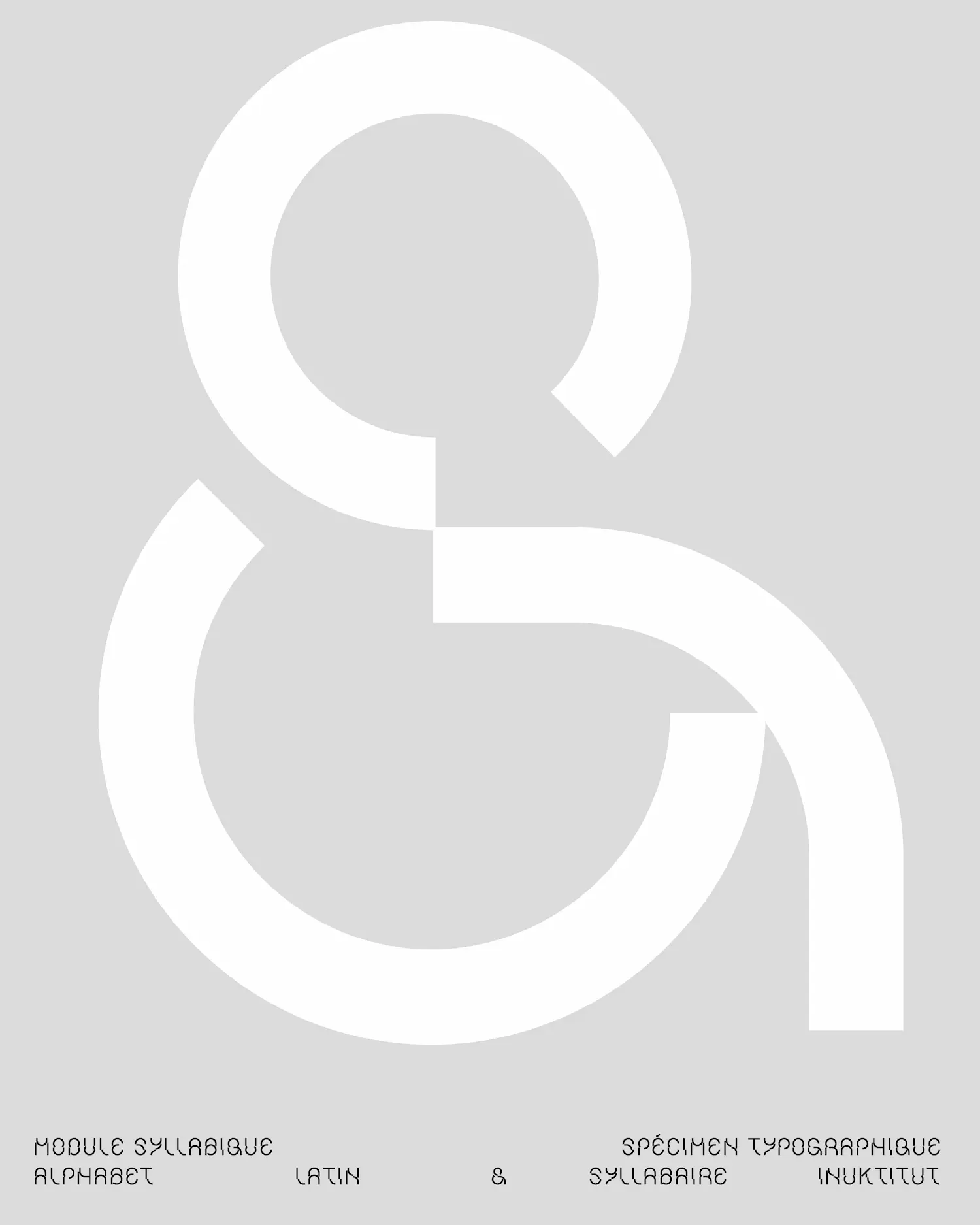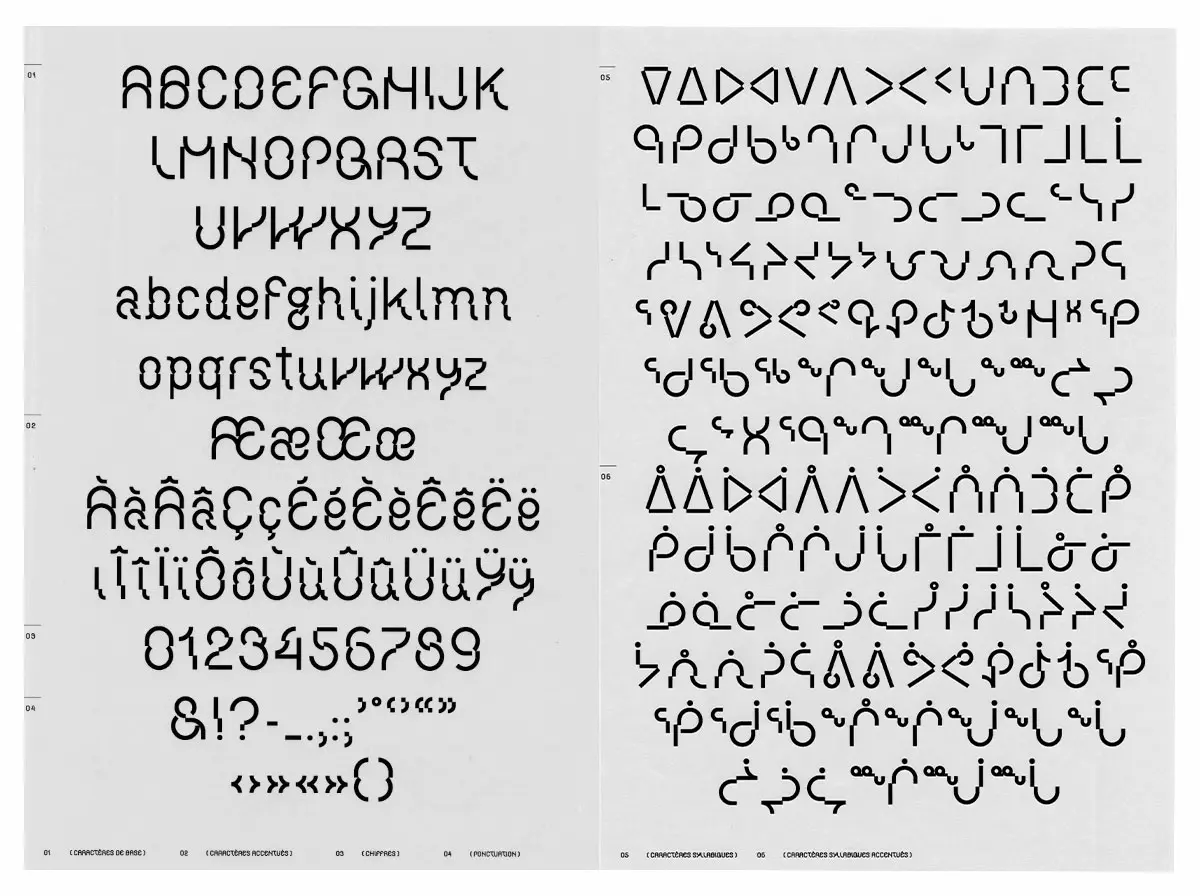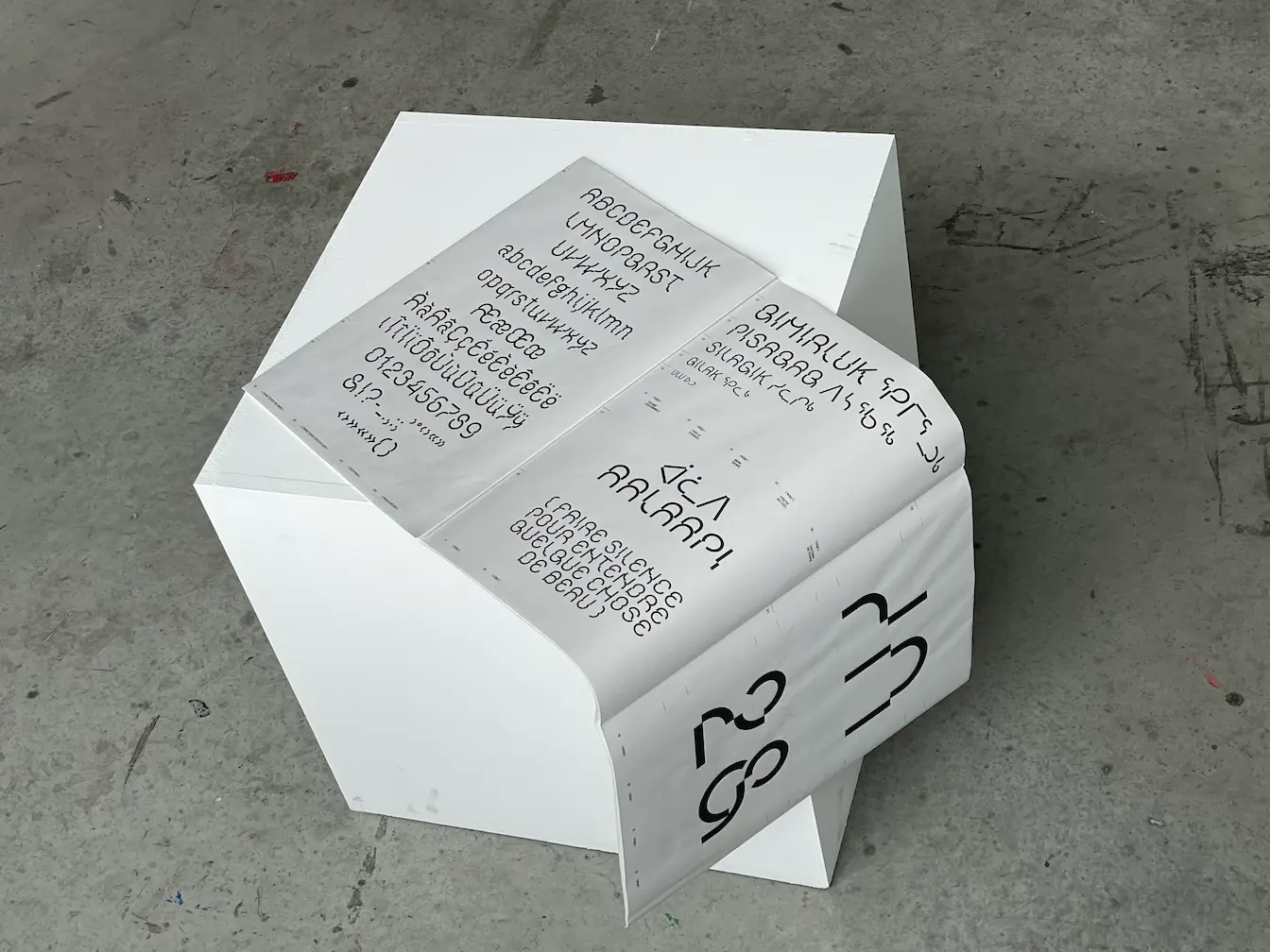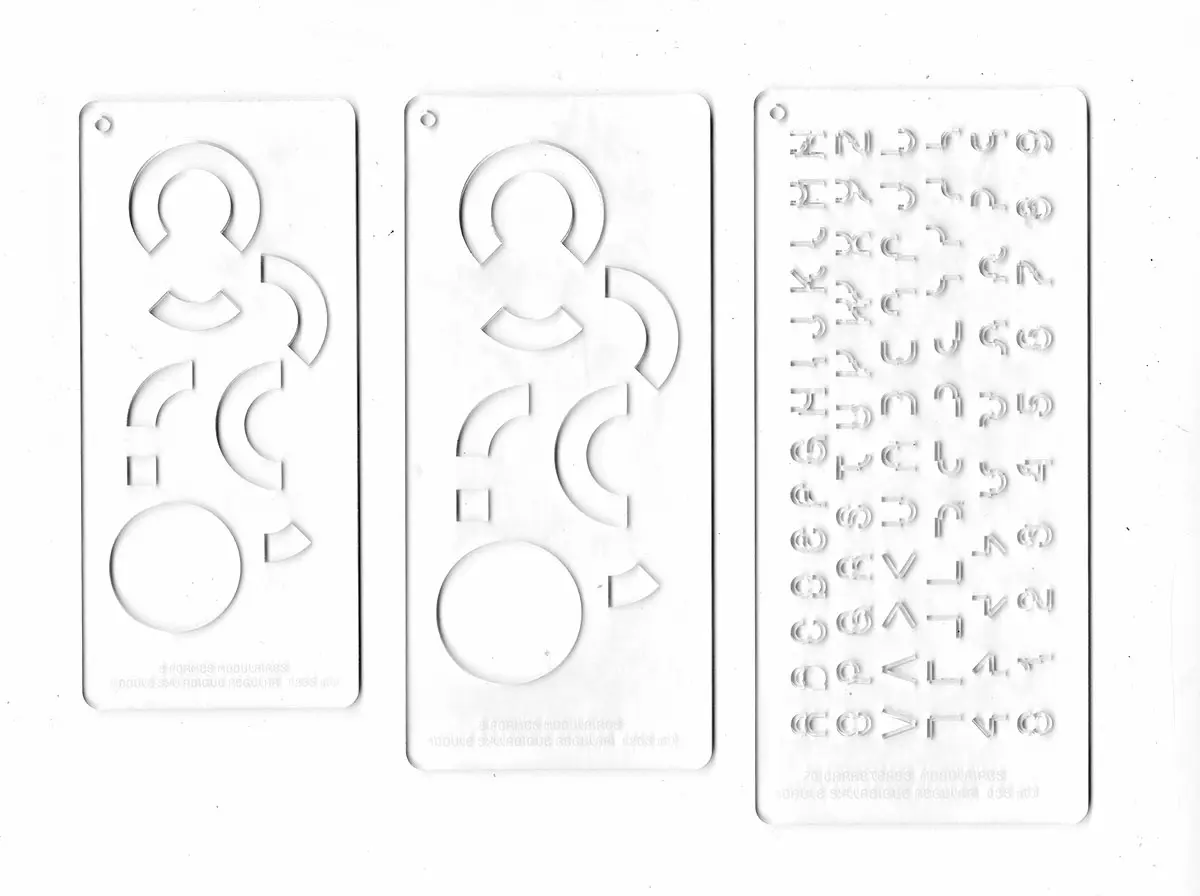
Module Syllabique
Module Syllabique est une création modulaire façonnée à partir de cercles et de bâtons, formes intrinsèques au syllabaire inuktitut. Elle déploie une esthétique à la fois expressive, géométrique et libre. Dans une démarche de rencontre, Module Syllabique aspire à offrir un espace significatif à la langue et à l’écriture inuktitut. Cette police de caractère cherche à tisser un lien harmonieux entre les systèmes d’écriture syllabique et latin, favorisant ainsi le dialogue et l’échange.
Descriptif
Alphabet syllabique
ᐃᐄᐅᐆᐊᐋᐱᐲᐳᐴᐸᐹᑉᑎᑏᑐᑑᑕᑖᑦᑭᑮᑯᑰᑲᑳᒃᒋᒌᒍᒎᒐᒑᒡᒥᒦᒧᒨᒪᒫᒻᓂᓃᓄᓅᓇᓈᓐᓯᓰᓱᓲᓴᓵᔅᓕᓖᓗᓘᓚᓛᓪᔨᔩᔪᔫᔭᔮᔾᕕᕖᕗᕘᕙᕚᕝᕿᖀᖁᖂᖃᖄᖅᕆᕇᕈᕉᕋᕌᕐᖏᖐᖑᖒᖓᖔᖕ
Alphabet romain
AaBbCcDdEeFfGgHhIiJjKkLlMmNnOoPpQqRrSsTtUuVvWwXxYyZz
Chiffres
0123456789
Ponctuation et symboles
!?"#$%&'()*,-./:;=@[\]`~«»‹›“”‘’–—¢£€¿¡#
Spécimen
• Page de spécimen montrant paragraphes brouillés, alphabet minuscule et majuscule, accents et chiffres.